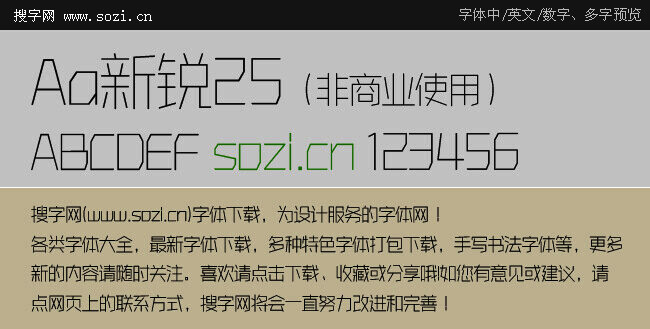
Aa新銳25
搜字網(wǎng)給大家提供一款A(yù)a新銳25(非商業(yè)使用)中文字體下載,該字體是一款中文藝術(shù)字體,字體共有七個字重,字體風(fēng)格簡潔大方,筆畫銳利新潮,散發(fā)一種青春的活力。適合圖書設(shè)計、包裝設(shè)計、海報設(shè)計等應(yīng)用(此字體為個人非商用版,商用可以聯(lián)系QQ:1006760504)。